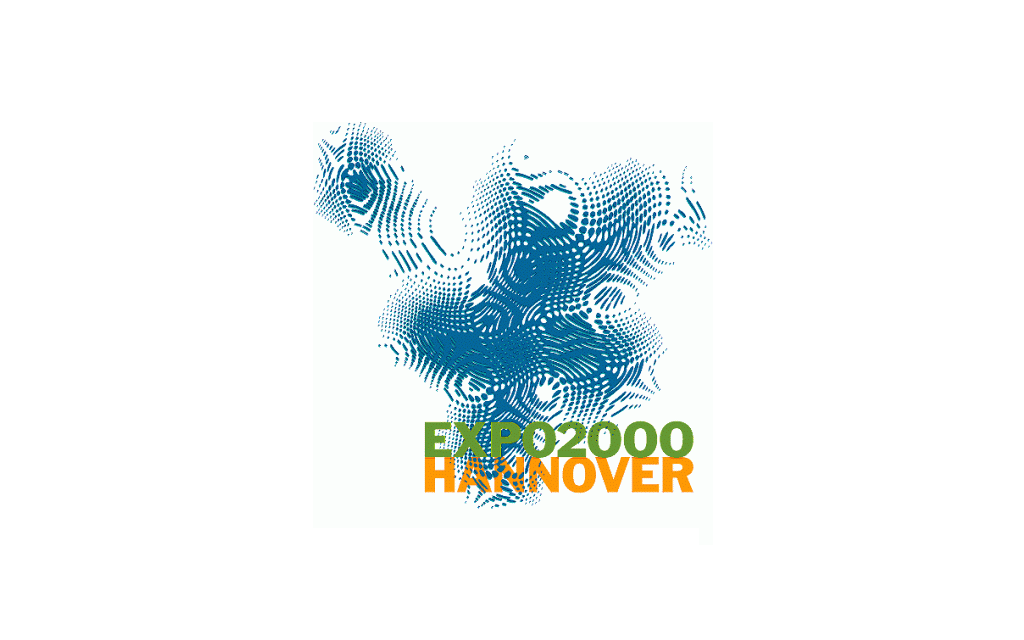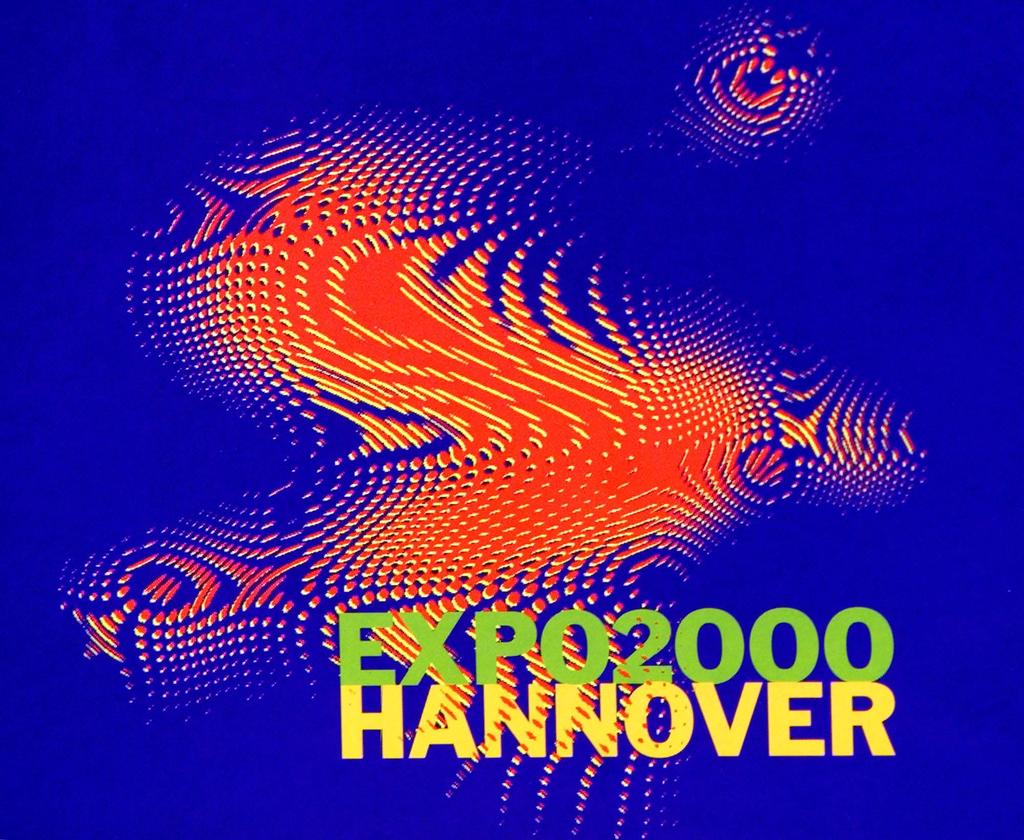
Wow, Ihr seid die Besten, das sind wirklich schöne, variantenreiche Beispiele, vielen Dank dafür! Im Detail kann ich nicht auf alles antworten. Aber es sei so viel gesagt: als Inspriation ist alles gut – selbst wenn schlecht gelöst, kann die Idee gut sein.
Das ist doch dieses kuriose Logo, das zu Boykottaufrufen in der arabischen/persischen Welt geführt hat, weil irgendjemand in dieser 2012 das Wort »Zion« lesen zu müssen meinte und gleich eine zionistische Weltverschwörung witterte. 8-)
Ich habe das erst gar nicht entdecken können, aber mit viel Phantasie, wenn man von oben nach unten liest und das eine oder andere Zeichen dreht … na ja. :neenee:
Einen Boykott wegen allgemeiner Häßlichkeit des Dingens hielte ich schon eher für gerechtfertigt.
Unbedingt. :nicken:
Tja, mir gefällt das in seiner Gesamtheit sehr gut.
Ich habe da weder Zion noch 2012 gelesen, für mich sieht das aus, wie ein krökeliger Breakdancer :-?
Das liegt aber vielleicht auch an den Farben :shock: